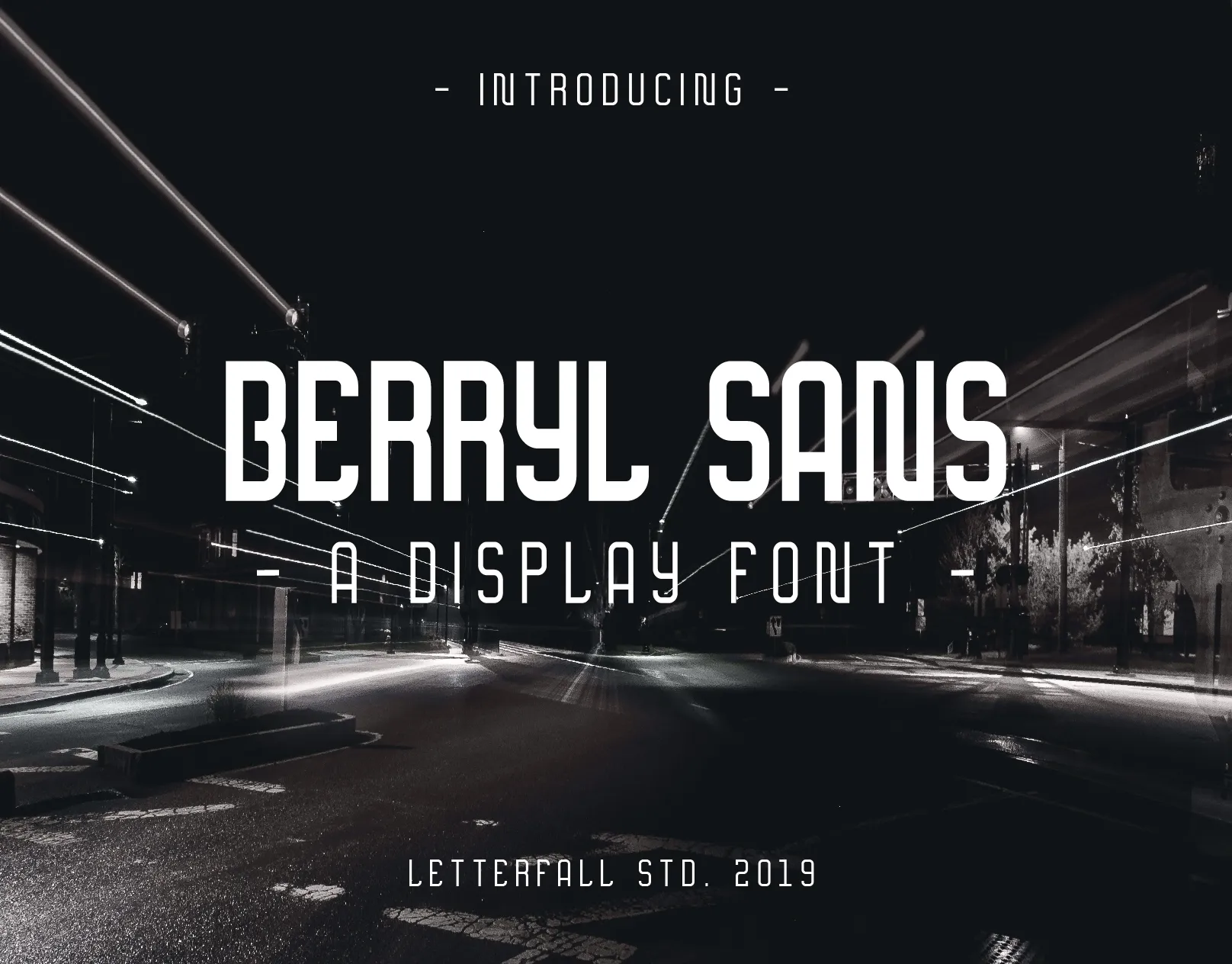
Berryl Sans Serif Font – Download Grátis
A Berryl Sans Serif é uma família de fontes sans serif que oferece um tom moderno e sofisticado. Ela foi criada por Hamilton e Berryl, designer de letras do LetterfallStd. Esta fonte fornece duas opções estilizadas: regular e bold, permitindo que você faça design único em poucos segundos. A Berryl Sans é uma família poderosa e elegante, ideal para criar designs diversos. Suas linhas finas e bem definidas criam um equilíbrio perfeito entre seriedade e facilidade de leitura. Combine o estilo regular com o bold, ou use apenas um dos estilos para destacar textos importantes em seus projetos. Se você está procurando uma fonte moderna que não seja totalmente digitada, a Berryl Sans é a escolha certa. Suas linhas delicadas e bem equilibradas permitem que você crie designs vibrantes e modernos sem ter de recorrer a um estilo mais rígido ou datado. Perfect para criar sites amigáveis ao usuário, layouts responsivos e até mesmo gráficos e logotipos com aparência sofisticada. Adquira a Berryl Sans Serif hoje e transforme seus projetos em algo singular e inovador. Experimente sua versão gratuita agora!